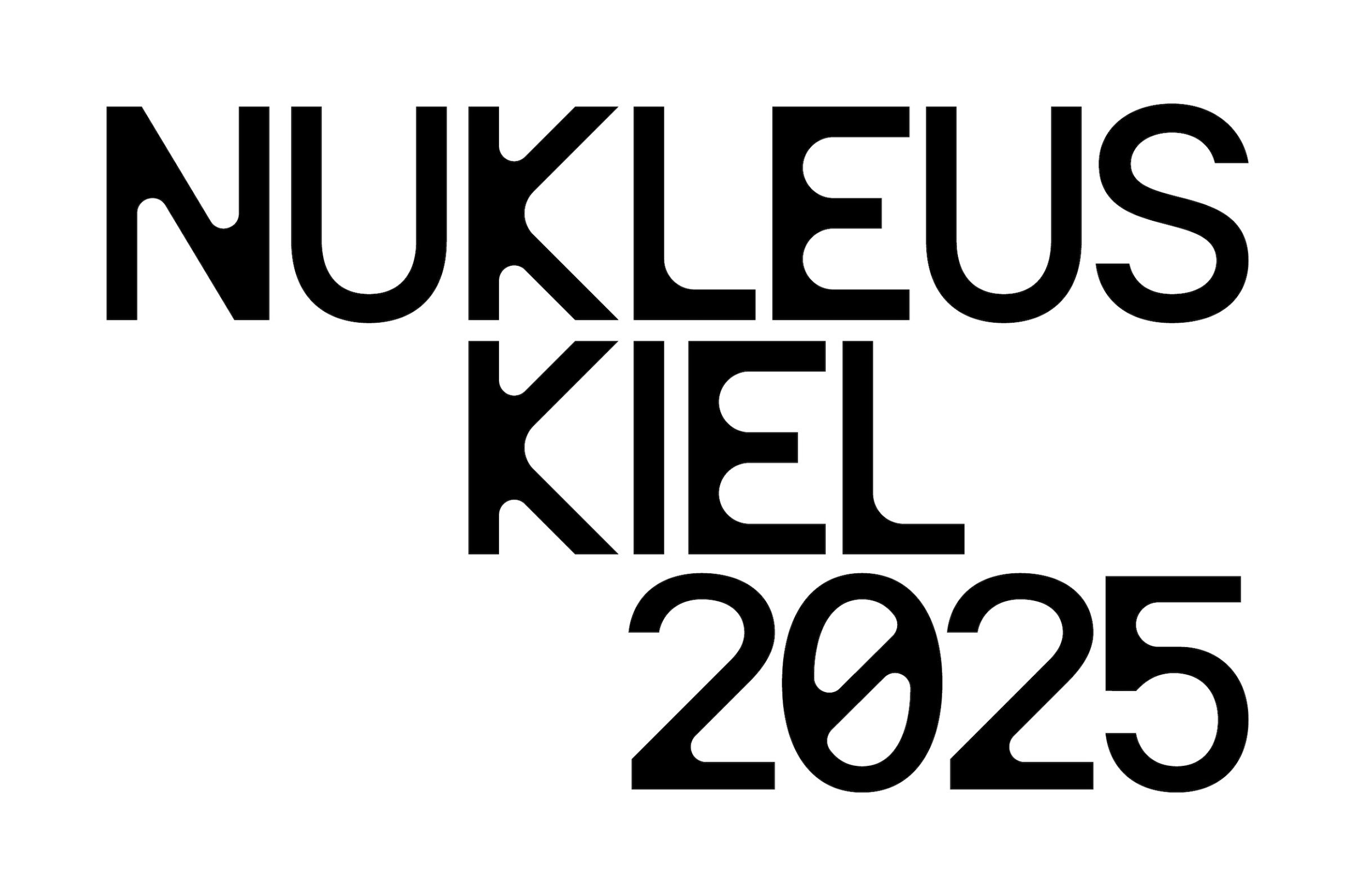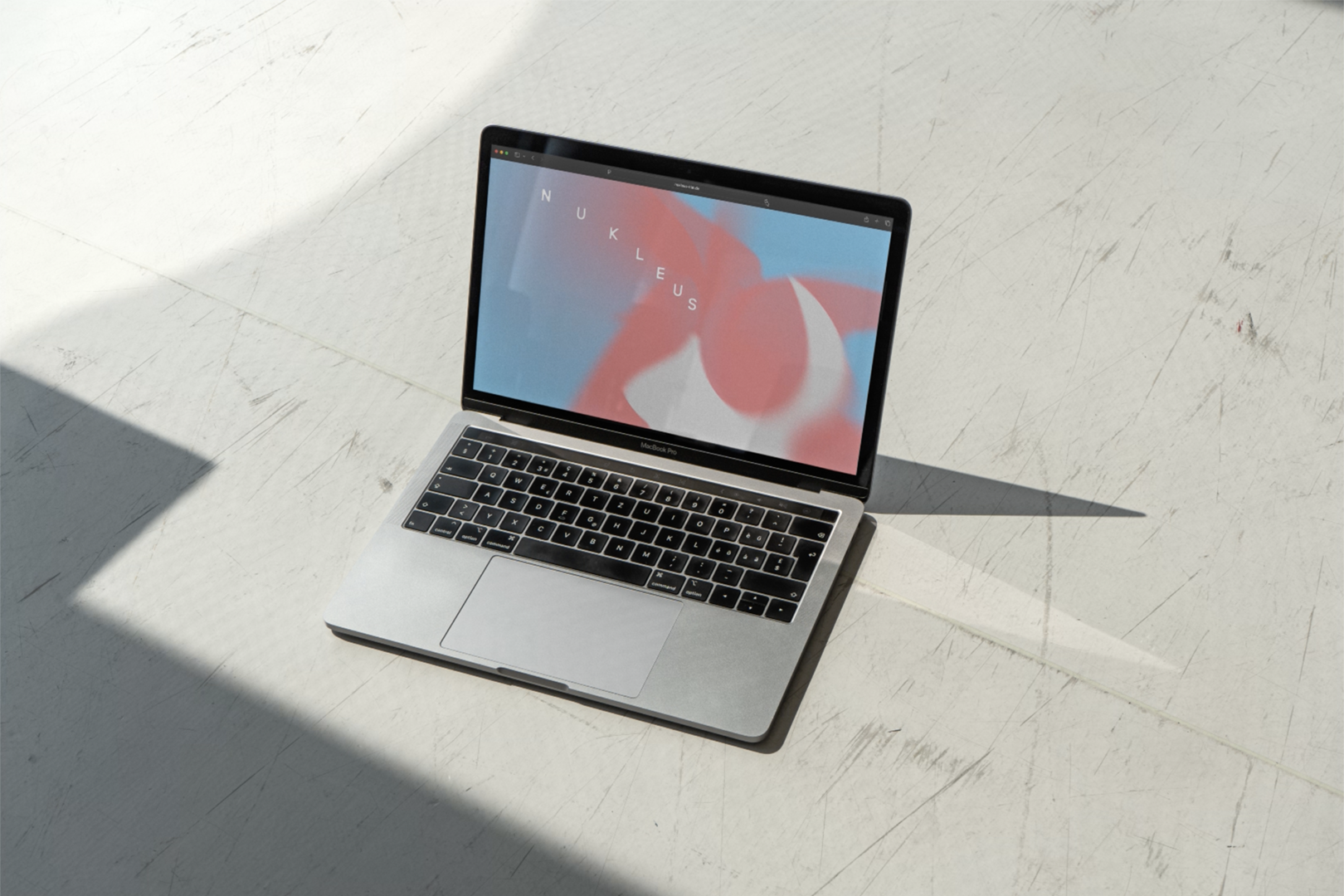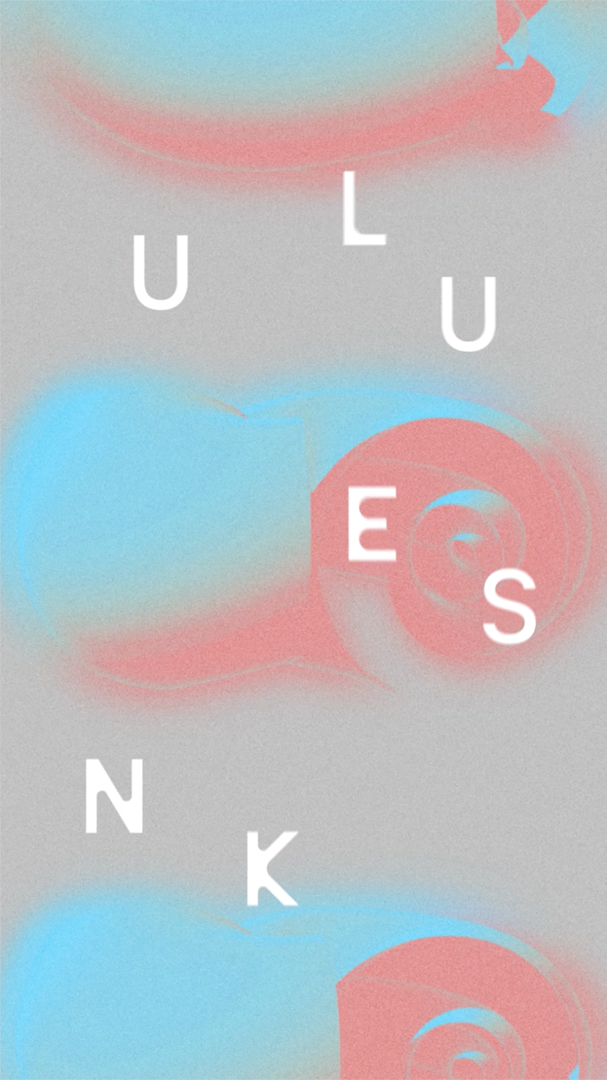
NUKLEUS Kiel ist ein interdisziplinäres Kunstprojekt, das den Stadtraum Kiels als Forschungsfeld versteht. Internationale Künstler*innen und lokale Studierende der Muthesius Kunsthochschule arbeiten über mehrere Monate hinweg an künstlerischen Interventionen, die Fragen nach urbaner Teilhabe, öffentlichem Raum und demokratischem Miteinander aufwerfen.
Die CI setzt sich mit dem Nukleus als Atomkern auseinander, als beginnender Moment von dem alles ausgeht. Dazu sind spiralenförmige Formen enstanden, die zum Kern führen. Die Farbgebung ist aufgeschlossen und freundlich. Das Logo ergänzt durch die geometrischen Formen der Letter den grafischen Entwurf. Auf der Website schweben die abstrakten Objekte durch den dreidimensionalen Raum und stellen so die Bewegung durch die Stadt Kiel dar. Eine klare Menuführung in form einer Liste öffnet neue Fenster, die sich frei über den Bildschirm verteilen, vergrößern und verkleinern lassen, um so die Interaktion mit den verschiedenen künstlerischen Interventionen zu verbildlichen.
Die dazu enstandene Webseite zielt darauf ab, den Besuchern schnell und übersichtlich Informationen zu vermitteln und verwendet dabei die Farbgebung und Formsprache der Corporate Identity. Die abstakt-spiralartigen Objekte schweben durch den dreidimensionalen Raumd der Website und stellen so die Bewegung durch die Stadt Kiel dar. Eine klare Menuführung in form einer Liste öffnet neue Fenster, die sich frei über den Bildschirm verteilen, vergrößern und verkleinern lassen, um so die Interaktion mit den verschiedenen künstlerischen Interventionen zu verbildlichen.
Im Rahmen des CIs sind sind ebenso Flyer und Social Media Inhalte entstanden.
Schrift: Neue Brücke von Due Studio